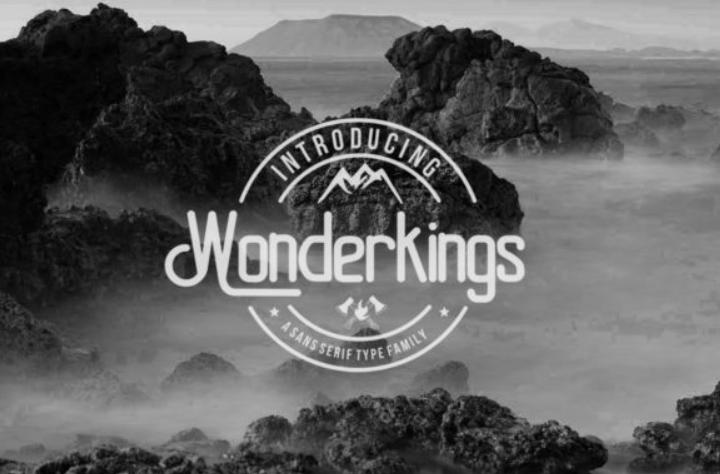
[Creativefabrica] Wonderkings Font (iyhulmonsta)
Wonderkings - чистый шрифт без засечек в винтажном стиле. Его можно легко сопоставить с невероятно большим набором проектов, поэтому добавьте его к своим творческим идеям и обратите внимание, как они выделяются среди них!